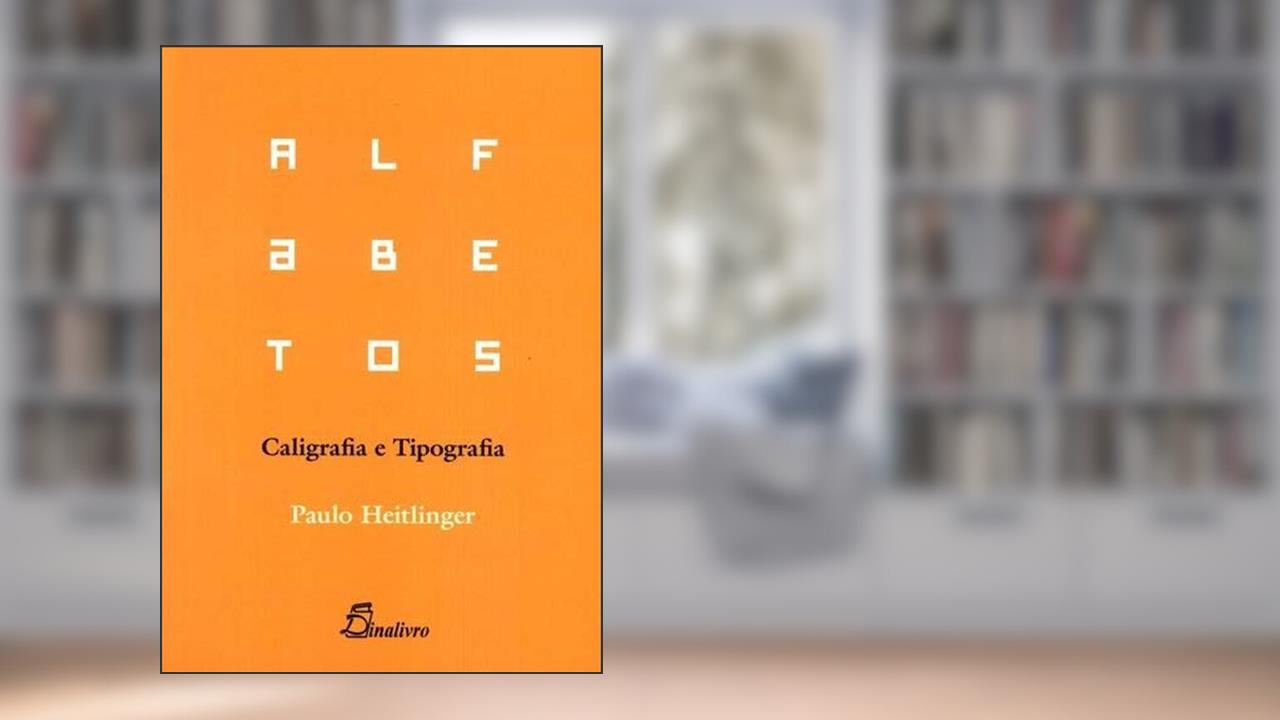
Alfabetos. Caligrafia e Tipografia, do autor Paulo Heitlinger
Alfabetos. Caligrafia e Tipografia
Paulo Heitlinger
Ler Alfabetos. Caligrafia e Tipografia, do autor Paulo Heitlinger
Alfabetos. Caligrafia e Tipografia não é apenas um livro; é uma verdadeira ode à expressão humana através da escrita. Ao percorrermos suas páginas, somos imediatamente envolvidos por uma fascinante tapeçaria de histórias, símbolos e significados que vão muito além das letras. O autor, Paulo Heitlinger, mergulha conosco nas profundezas da caligrafia e tipografia, convocando nossas emoções e despertando um interesse visceral por algo que, muitas vezes, consideramos corriqueiro: a escrita.
Histórias de amor, revolta e transformação se entrelaçam às diferentes formas de letras que, sob a batuta de Heitlinger, tornam-se protagonistas neste espetáculo literário. A tipografia, geralmente vista como um mero detalhe técnico na comunicação, é aqui elevada ao status de arte. Entre as várias curiosidades, é impossível não se perguntar: de que forma a letra que você escolhe para um convite ou um livro pode influenciar o que o receptor sente? Você já parou para pensar que cada traço de uma caneta ou cada pixel de uma fonte digital carrega emoções e intenções que podem moldar uma experiência? As páginas de Heitlinger fazem você questionar sua relação com esses elementos.
Os leitores não hesitam em expressar suas opiniões sobre essa obra monumental. Para alguns, a riqueza de detalhes e a profundidade do conteúdo são verdadeiras aulas de sensibilidade estética e técnica. Outros, no entanto, criticam a densidade do material; chamando-o de excessivamente técnico, como se a complexidade do tema fosse uma barreira e não um convite a um novo mundo. Mas não deixa de ser um alvoroço de ideias, não é mesmo? Criar a partir do que está ao nosso redor, como as letras, é revolucionário.
O contexto histórico desta obra é, sem dúvida, um dos aspectos que a tornam única. Publicada em um período em que a digitalização ameaçava redefinir os modos de comunicação, Alfabetos. Caligrafia e Tipografia ergue-se como um baluarte contra a homogeneização das expressões gráficas. Heitlinger nos faz ver que, mesmo no turbilhão das inovações tecnológicas, as letras manuscritas e as tipografias escolhidas ainda são vitais para a construção de identidades e narrativas.
É inegável que, ao explorar esta obra, você não apenas se delicia com a beleza da linguagem escrita, mas também se depara com um chamado à reflexão sobre como comunicamos nossos pensamentos e sentimentos. As palavras se desdobram como uma dança de sentidos, convidando você a participar desta celebração da criatividade e individualidade.
O que você está esperando para descobrir como as letras podem provocar emoções intensas e profundas? A sensação de sua ponta deslizando sobre o papel, a forma como as fontes escolhidas podem trazer à tona sentimentos e memórias... Alfabetos. Caligrafia e Tipografia é uma explosão de conhecimento que te incita a repensar a experiência da leitura e da escrita! Prepare-se para ser desafiado, revigorado e, quem sabe, até mesmo transformado, principalmente porque as letras que você não conhece ainda estão esperando por você. 🌟